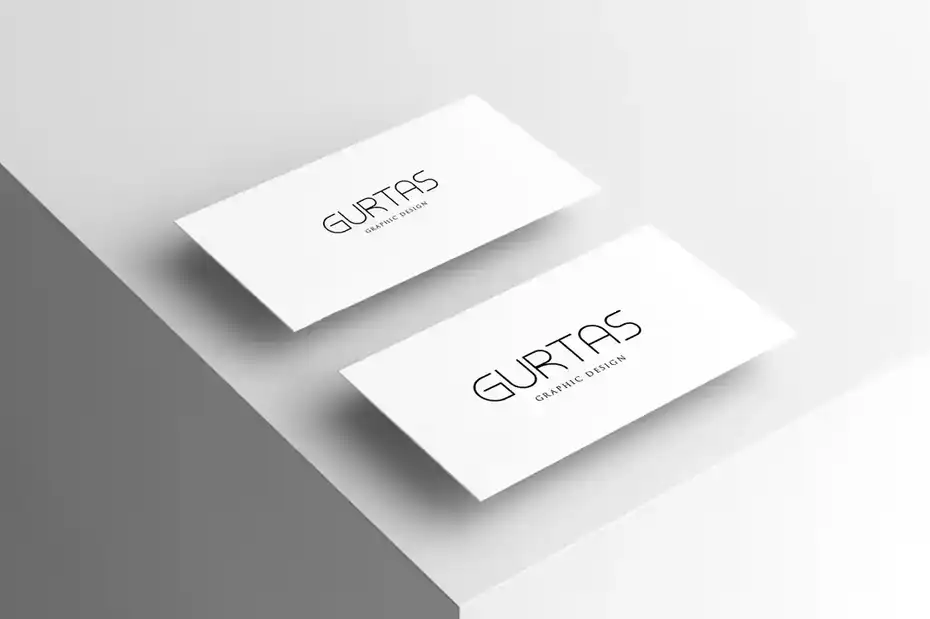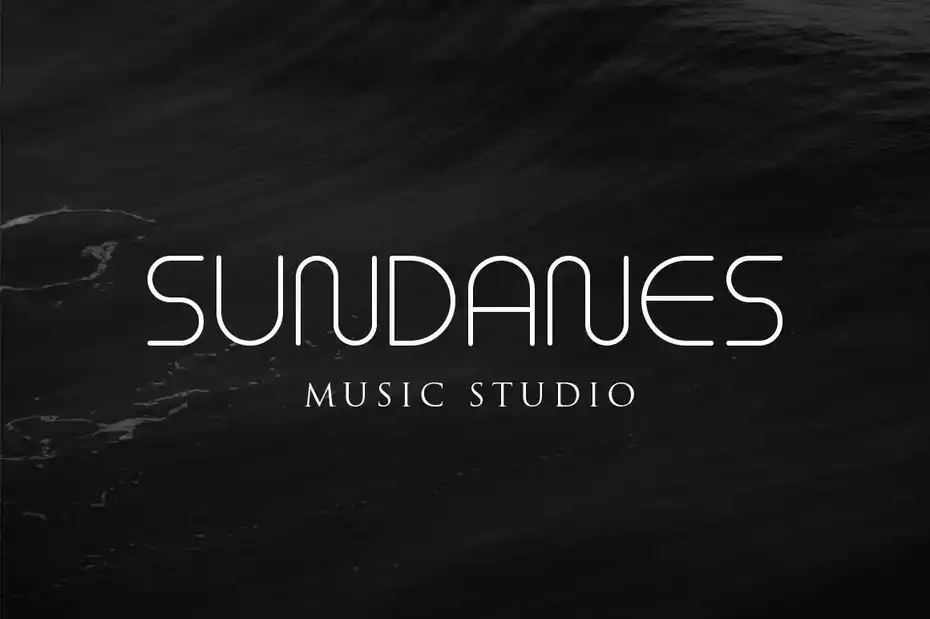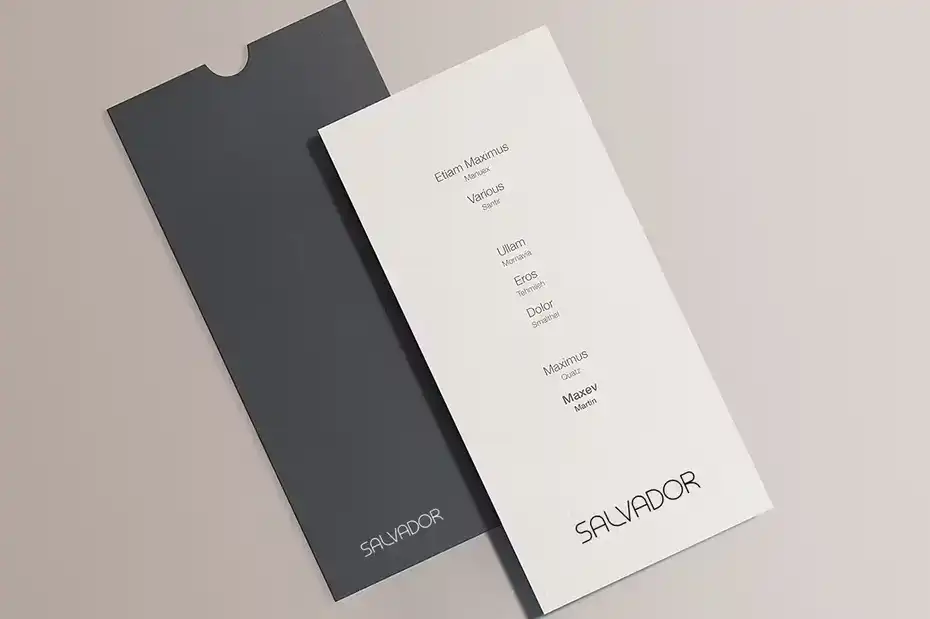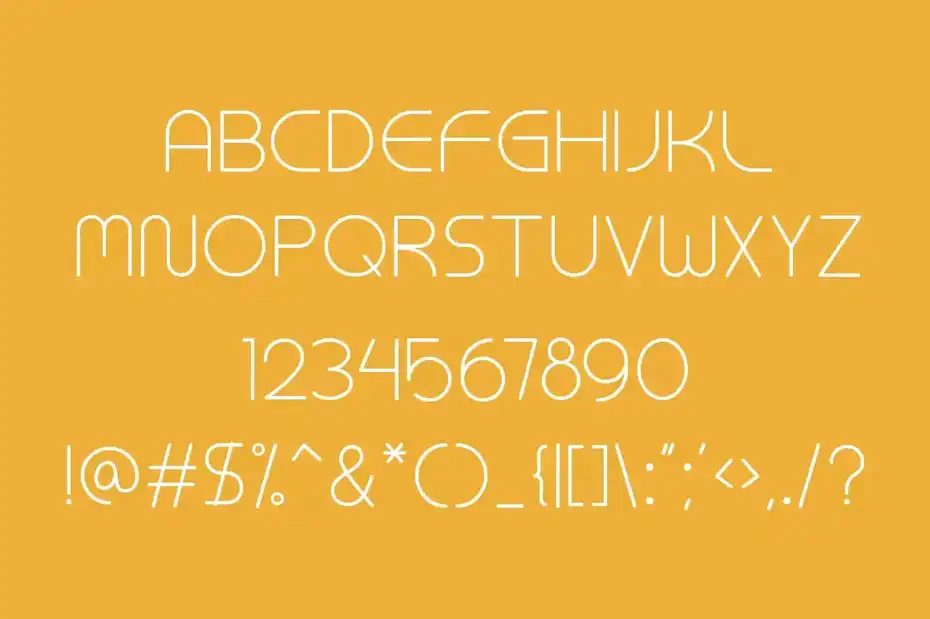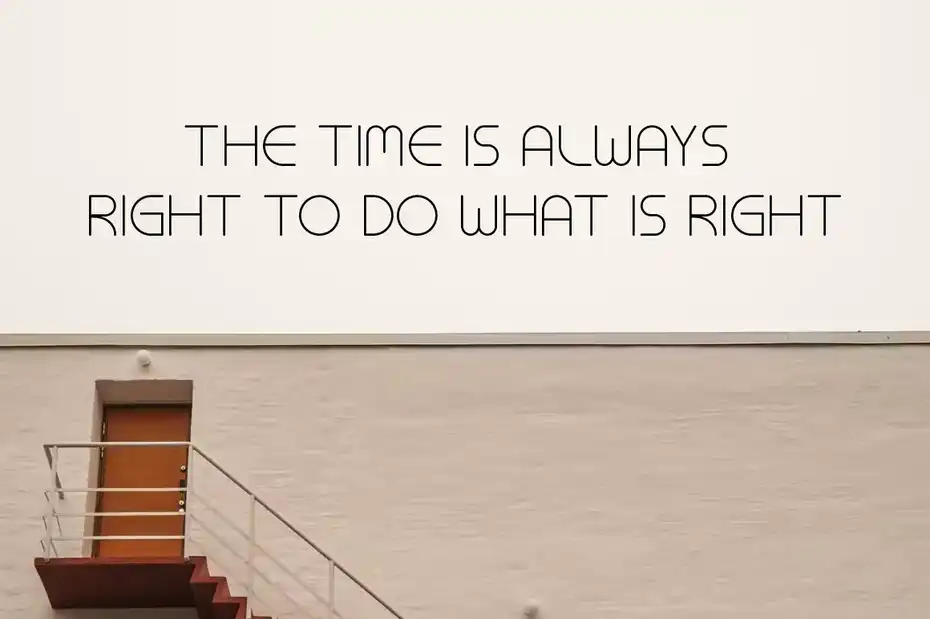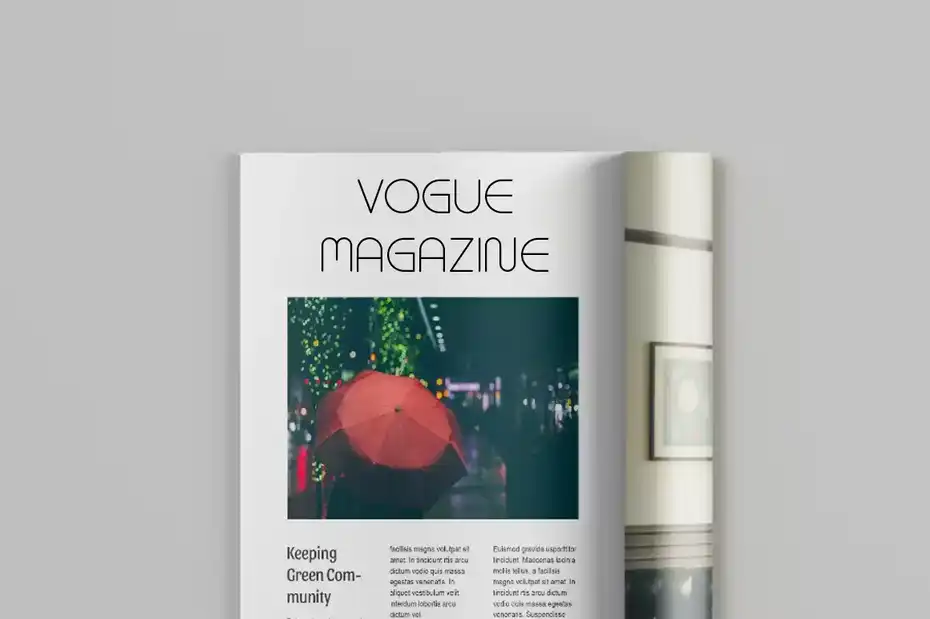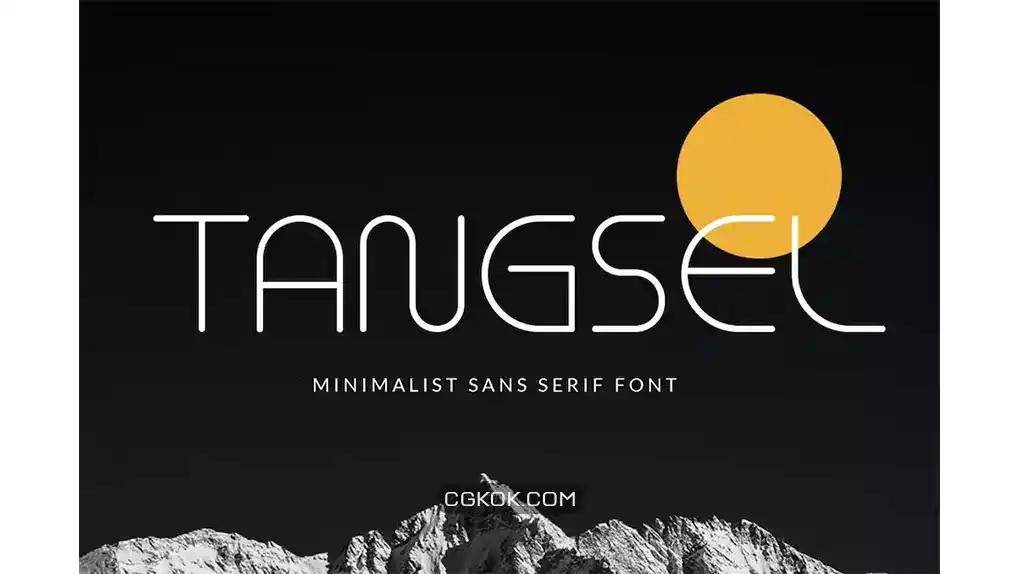
دانلود فونت انگلیسی مدرن Tangsel – Minimal font
فونت انگلیسی مدرن Tangsel – Minimal font : این مجموعه شامل یک فونت انگلیسی مدرن است که کارت ویزیت و غیره مناسب میباشد.